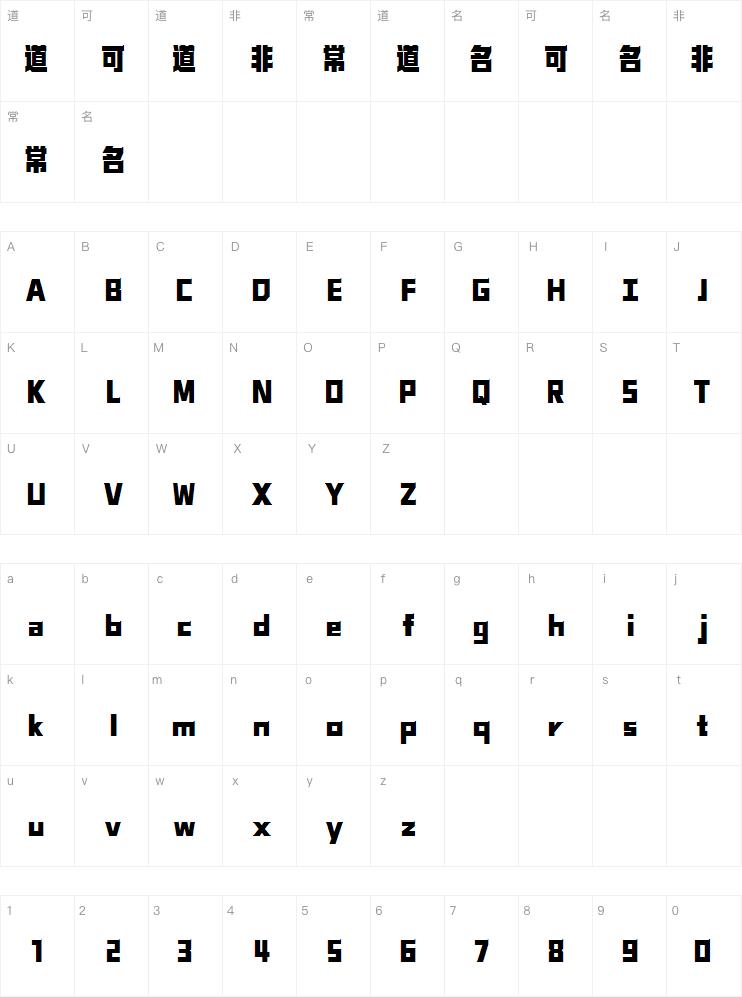
山海先锋黑w
山海先锋黑,是一款全新的字体,包含汉字9169个,符号200+个。该字体是一款综艺标题黑体字体,是一款具有强劲视觉冲击力的综艺风格标题字体。字形充实填满整个字框,造型硬朗,直线的笔画构成坚实有力,简洁明了的笔画切角;字形比例按照宽高8:10的比例设计,使得字体显高;同时笔画带有尖角装饰,使得字形带有律动感,带来强有力的视觉冲击效果。该字体在综艺体的基础上做了诸多创新,使得该字体既有着流动的美感,又有着端肃的凝重,在正式用字场合落落大方,在日常使用环境中不失亲切友好,能够在保留综艺体基本特征的基础上更能适应当下时尚潮流的需要,助力各大新产品夺取标题主战场。